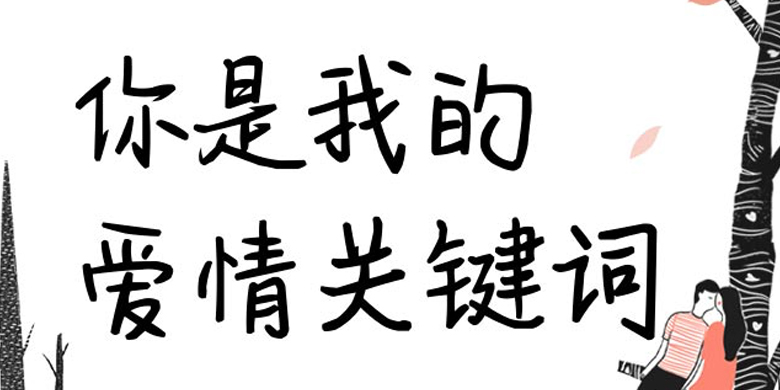
方正手迹-你是我的爱情关键词
方正手迹-你是我的爱情关键词,这款字体结构工整、笔画清晰,兼顾美观与易读性,适用于标题、正文、海报、包装、LOGO 等多种场景。字形优雅稳定,风格百搭耐看,适配日常排版与创意设计,让文字呈现更舒适、更具质感。方正手迹-你是我的爱情关键词一笔一画,皆是细节,以均衡的比例、流畅的线条打造舒适视觉体验,字形端正大气,风格简约现代。无论是商业设计、品牌宣传还是日常排版,都能轻松驾驭,让文字更有格调与力量。方正手迹-你是我的爱情关键词字体下载。
作者一笔一划的行笔,更显得真诚,难能可贵。笔画稍显笨拙,也和爱情一般,笨拙但是小心翼翼,阅读起来舒适感极强。适用于少年儿童类的书刊、品牌广告和产品包装设计,以及社交网络的个性化用字。